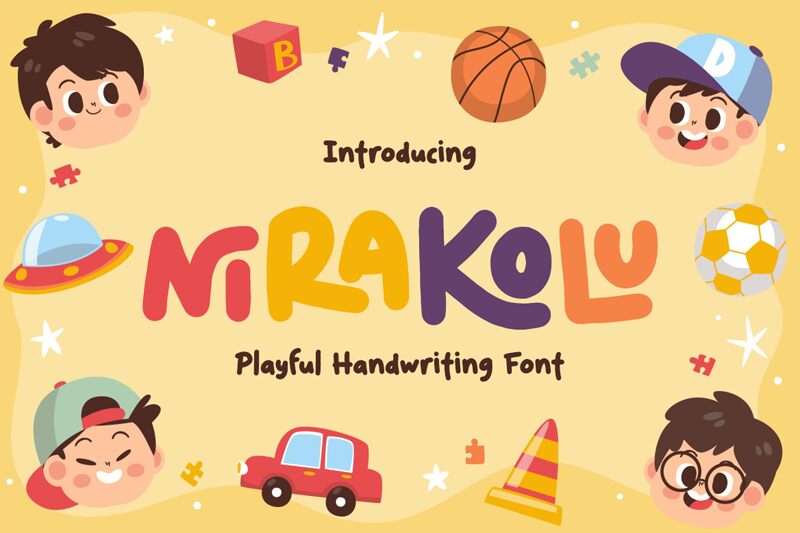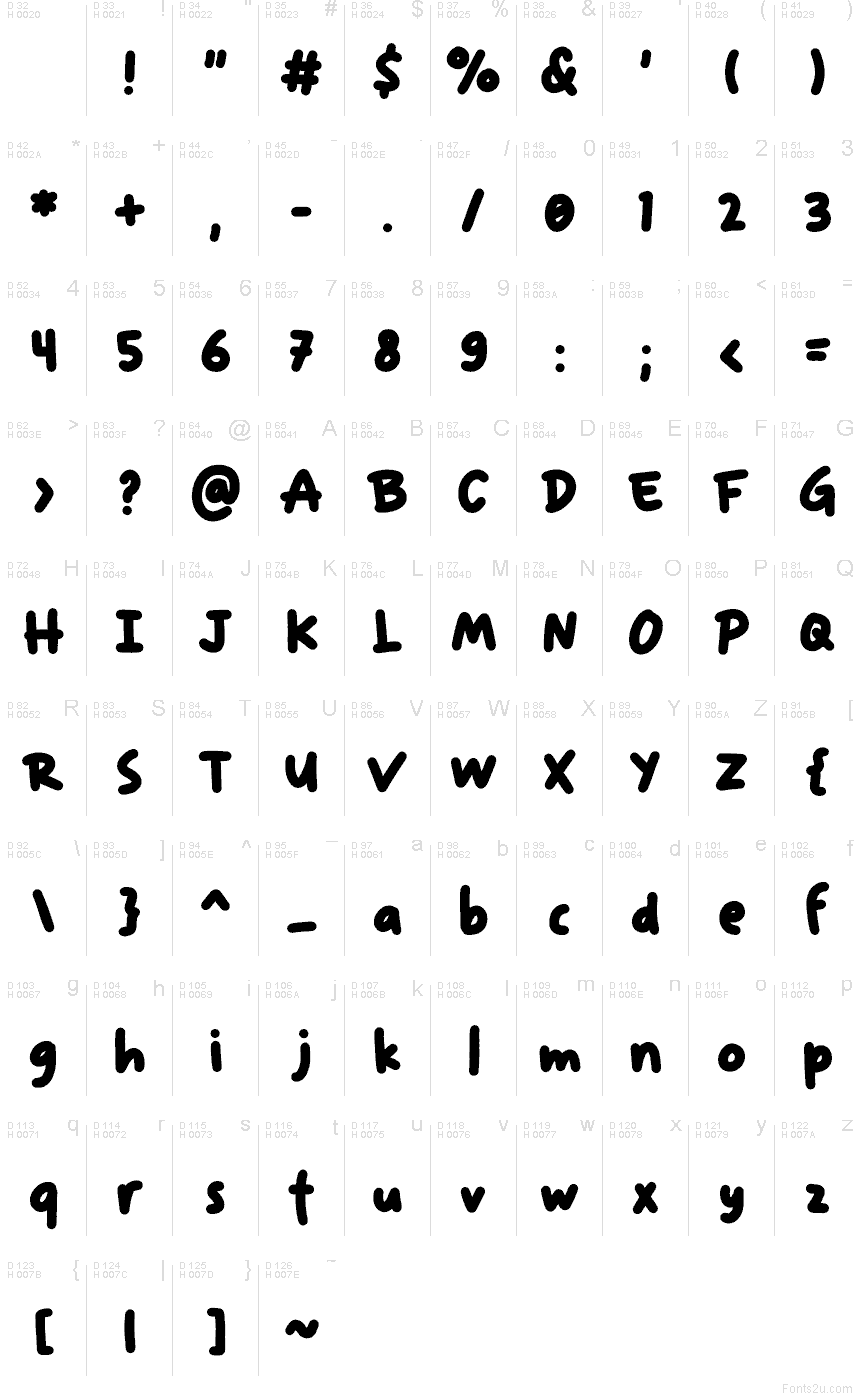
Nirakolu, di Shanaf Studio, è un font gratuito in stile fumetto con lettere grandi e arrotondate e un aspetto dinamico, disegnato a mano. Le forme appaiono morbide e amichevoli, con tratti spessi, angoli arrotondati e un ritmo leggermente irregolare che mantiene il font giocoso invece che troppo perfetto.
È ideale per copertine di libri per bambini, confezioni di snack, poster scolastici, schermate di app e grafiche vivaci per i social media, dove un font gratuito deve trasmettere calore piuttosto che perfezione tecnica. Usalo per titoli brevi, targhette e loghi, poiché le forme gonfie e il design casual conferiscono anche alle parole più semplici una presenza allegra e spontanea.